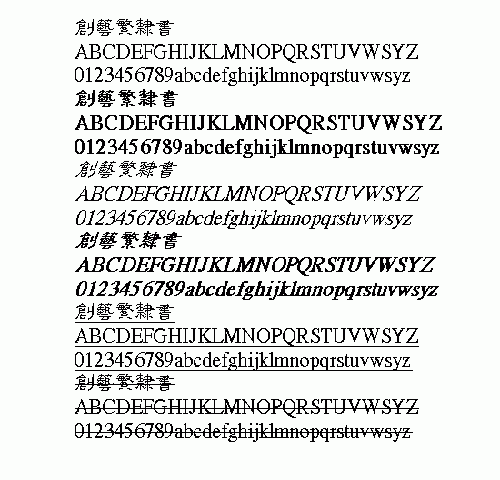
創(chuàng)藝繁隸書(shū)字體是創(chuàng)藝字體庫(kù)中的免費(fèi)字體文件,這款字體多用于設(shè)計(jì)帶有藝術(shù)效果的文字內(nèi)容。雖為繁體,因具備了隸書(shū)字體的風(fēng)格特征,所以使用到的也比較多!
隸書(shū),有秦隸、漢隸等,一般認(rèn)為由篆書(shū)發(fā)展而來(lái),字形多呈寬扁,橫畫(huà)長(zhǎng)而豎畫(huà)短,講究“蠶頭雁尾”、“一波三折”。根據(jù)出土簡(jiǎn)牘,隸書(shū)始創(chuàng)于秦朝,傳說(shuō)程邈作隸,漢隸在東漢時(shí)期達(dá)到頂峰,上承篆書(shū)傳統(tǒng),下開(kāi)魏晉、南北朝,對(duì)后世書(shū)法有不可小覷的影響,書(shū)法界有“漢隸唐楷”之稱(chēng)。